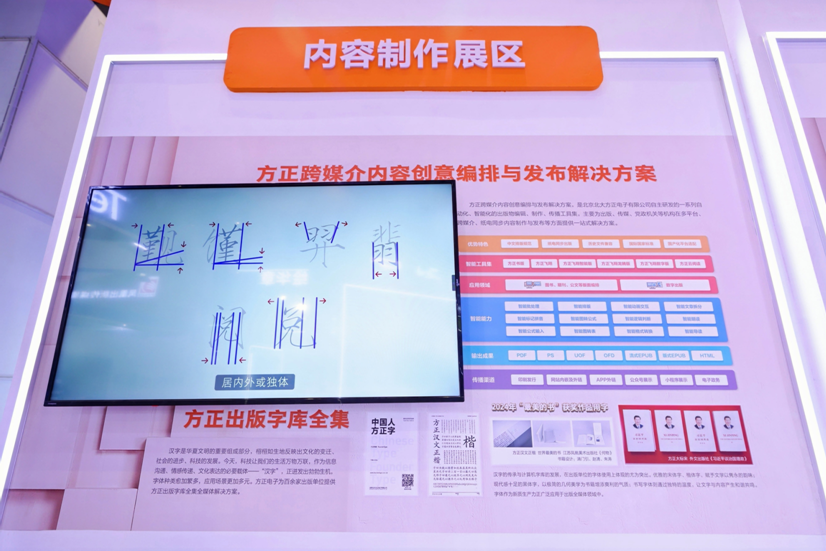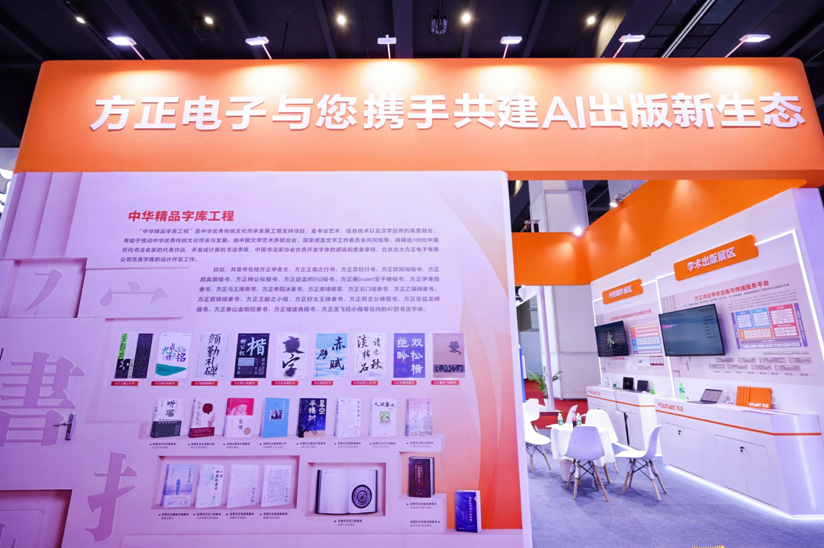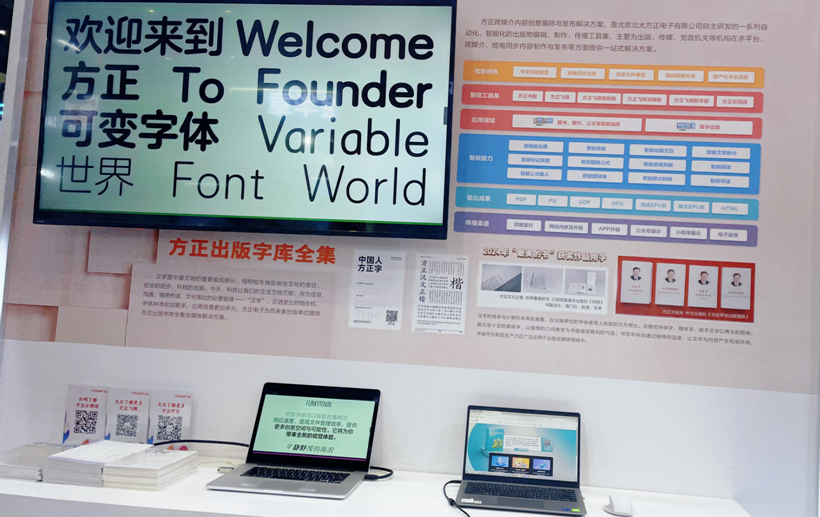
共建AI出版新生态 方正电子携重磅产品和技术亮相2025数博会
全流程赋能 构建AI出版新生态
8月28日至31日,第十五届中国国际数字出版博览会(以下简称“2025数博会”)在河南郑州国际会展中心开幕。本届数博会以“数实相融 智赢未来”为主题,吸引了国内外超600家出版机构、数字技术企业参展,集中展示数字出版领域的新成果、新技术与新趋势。展会同期设置了1个主论坛、4个专题论坛和系列现场活动。
作为出版行业技术领军企业,北京北大方正电子有限公司(简称“方正电子”)受邀参展,并参加了中国出版协会主办的“第九届数字出版创新发展论坛”以及“第二届《中国数字出版》青年论坛”两大专题论坛,与业内专家、合作伙伴等共同探索AI赋能下智能出版的新趋势、新动能。
方正电子副总裁刘长明为参观领导介绍了方正电子赋能出版全流程的先进产品和技术,并重点介绍了跨媒介创意编排软件在书报刊排版、信创国产化替代以及中华精品字库工程研发成果。
在数字化技术深度赋能出版业的当下,人工智能技术的高效应用已成为行业革新的关键驱动力。本届数博会,方正电子紧扣展会主题,设置了“AI大模型”“融合出版”“学术出版”“按需出版”以及“内容制作”五大展区,全面呈现方正电子以科技创新驱动行业变革、构建AI出版新生态的探索与实践。
传递汉字之美、丰富文化表达
科技让万物万联的今天,作为信息沟通、情感传递、文化表达的必要载体——“汉字”,正迸发出勃勃生机,字体种类愈加繁多,应用场景更加多元。汉字的传承与计算机字库的发展,在出版单位的字体使用上体现得尤为突出。字体作为新质生产力正广泛应用于出版全媒体领域中。为充分展现汉字及字体的艺术魅力,现场还展出了中华精品字库工程已经发布的王羲之行书、欧阳询楷书、苏轼行书等精品书法字体以及这些字体在出版领域的应用案例。通过将人工智能技术与书法艺术相结合,方正电子不仅推动了传统文化的传承与发展,还为传统文化赋予了新的时代内涵。
本届数博会,方正电子不仅成功展示了在出版领域的全新成果、前沿技术以及实践案例,更通过“第九届数字出版创新发展论坛”“第二届《中国数字出版》青年论坛”等活动上的精彩分享,与行业同仁一起探索、共建AI出版新生态。未来,方正电子将继续以技术创新为驱动,深化与业界伙伴的合作交流,不断探索出版业务链全流程转型升级,为出版融合深度发展贡献力量。